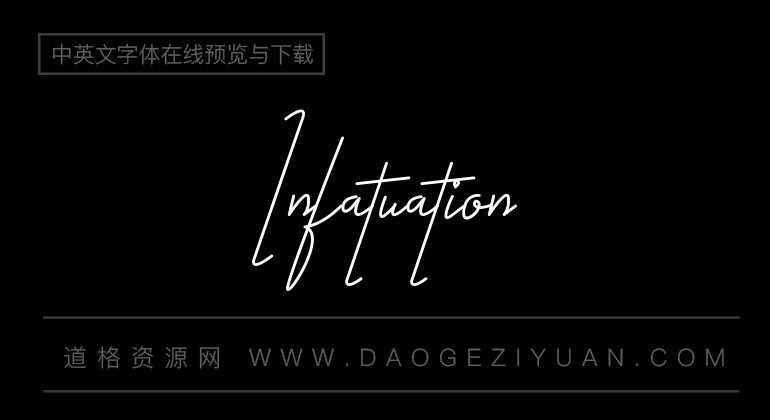
Infatuation 是一款由Fontfabric字体工作室推出的细腻浪漫的欧式新字体,具有明显的灵感来自欧洲古典艺术风格,拥有流动的线条和自然的节奏,构成了一种优雅精致的字体形态。它的曲线流畅,细节处理精细,让字体的表现力更加强烈,具有非常好的可读性。它的体积较小,易于安装和使用,并且可以在多种设计软件中使用,非常适合用于品牌标识、海报、包装、网页等设计项目中。内容介绍
Infatuation是一款非常不错的手写艺术字体,具有很好的视觉感,适合于文化类的宣传设计、商业类品牌的广告和产品包装设计以及个性化文字排版等较多场景。